Design Cutsで、新しいデザイン素材バンドルが発売されました。
今回のバンドルは「The Treasure Trove of Fonts for Typography Lovers」。表現の引き出しが増える欧文フォントが世界中から集まりました。
- ウェイト違いを多数収録したビッグファミリー書体収録
- リガチャ(合字)やスウォッシュ(飾り)なども充実
- 多くのフォントが英語、スペイン語、フランス語、ドイツ語をはじめとした多言語に対応
「The Treasure Trove of Fonts for Typography Lovers」の気になる中身は?
流行はおさえておきたい!コントラスト強めのセリフフォント
最近流行の、ボディの太さにメリハリがきいたセリフフォント。いまどきのデザインフォントも、バンドルならお得なプライスで試すことができます。
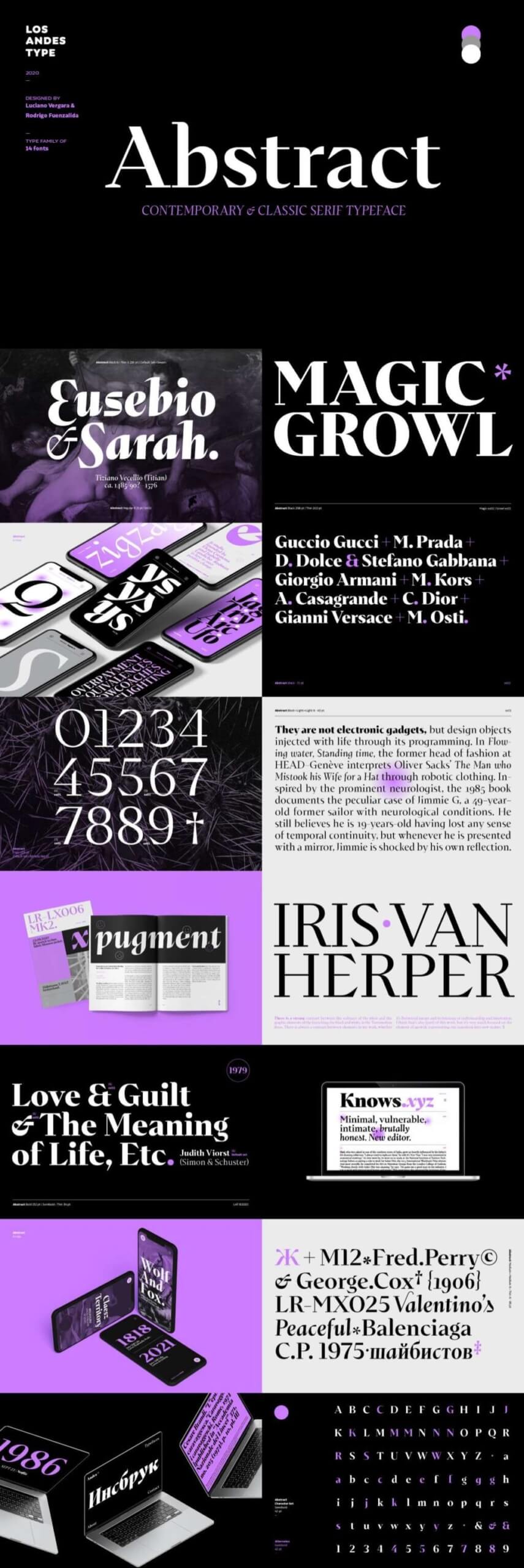
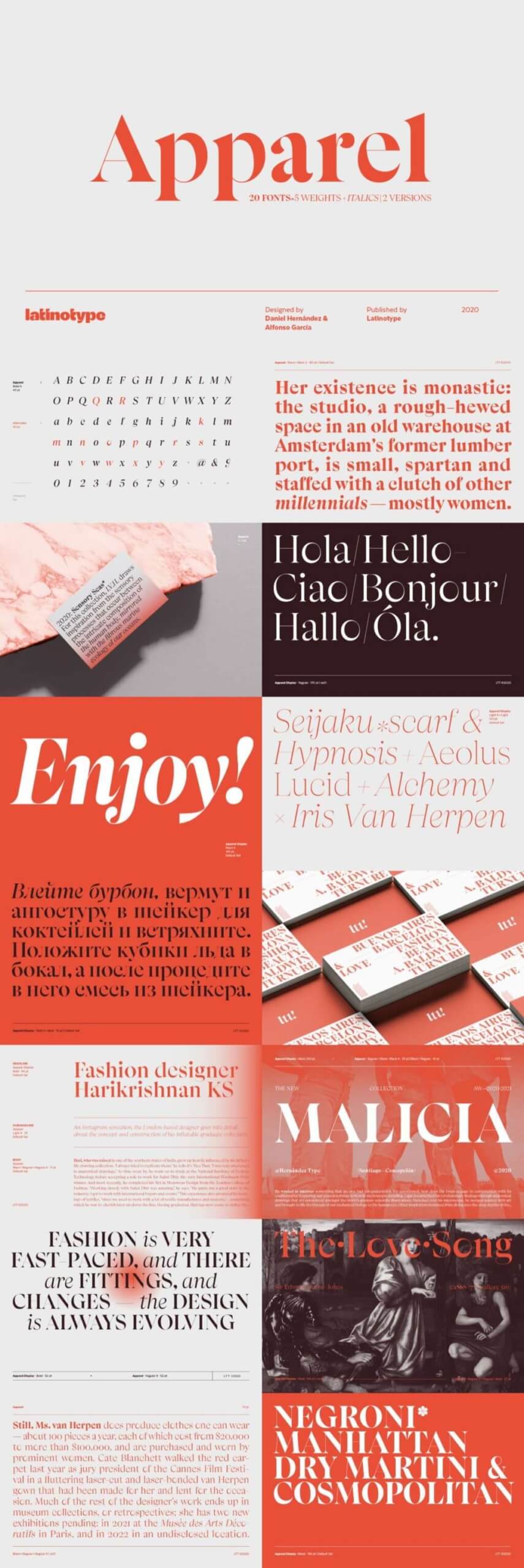
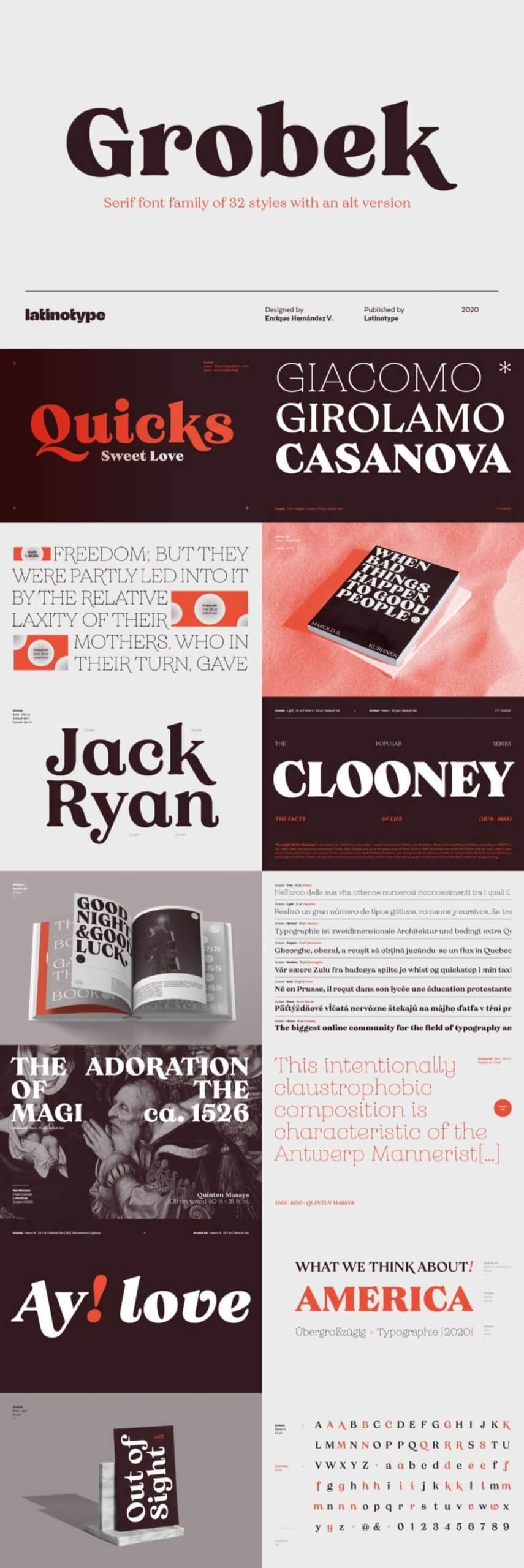
ウェイト違いが豊富なビッグファミリー書体
何種類ものウェイトをそろえたビッグファミリー書体は、繊細なウェイトの使い分けが必要なデザインワークで重宝します。The Treasure Trove of Fonts for Typography Loversも、そんな便利なビッグファミリーを収録。通常価格が300ドル以上のものも、このバンドルなら他のフォントとまとめて29ドルで揃えられます。
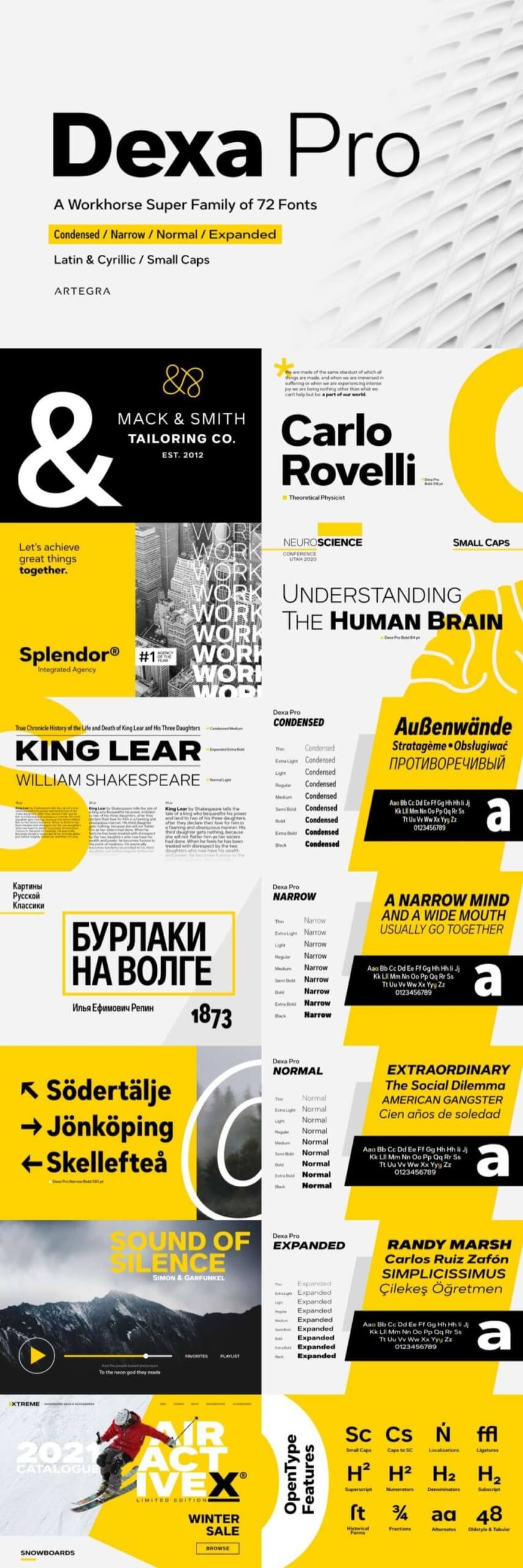
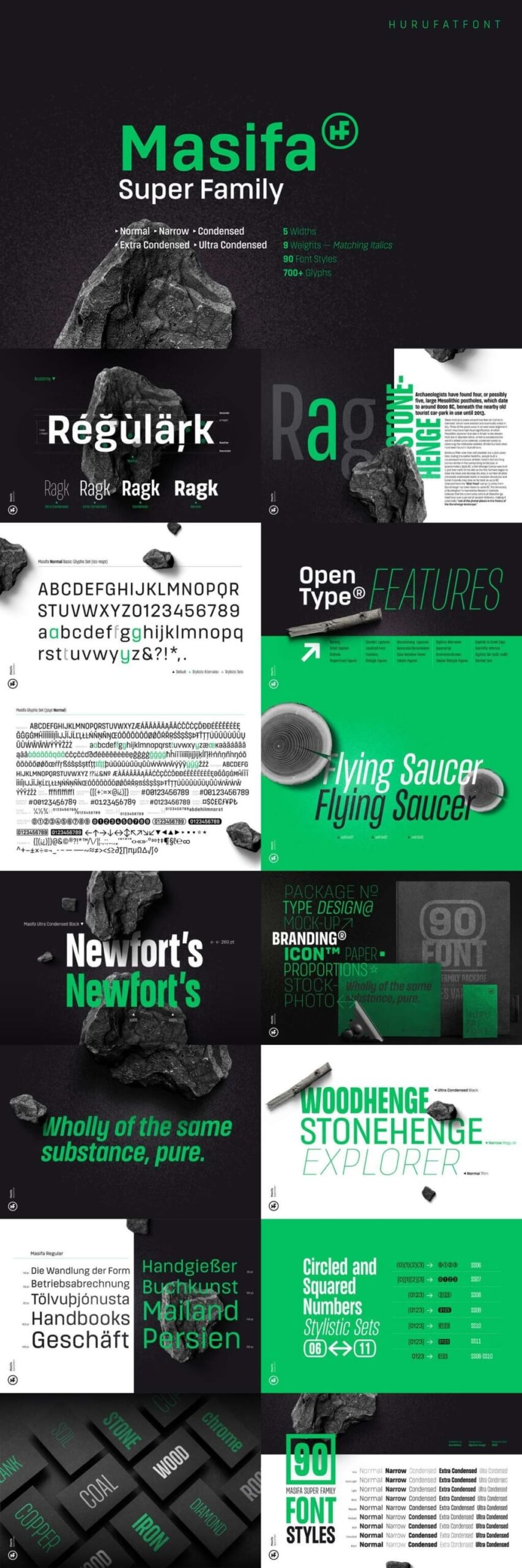
小さくても読みやすい!実用的なサンセリフフォント
小さい文字が多い媒体に便利なサンセリフフォント。The Treasure Trove of Fonts for Typography Loversにも様々なサンセリフフォントを収録しています。
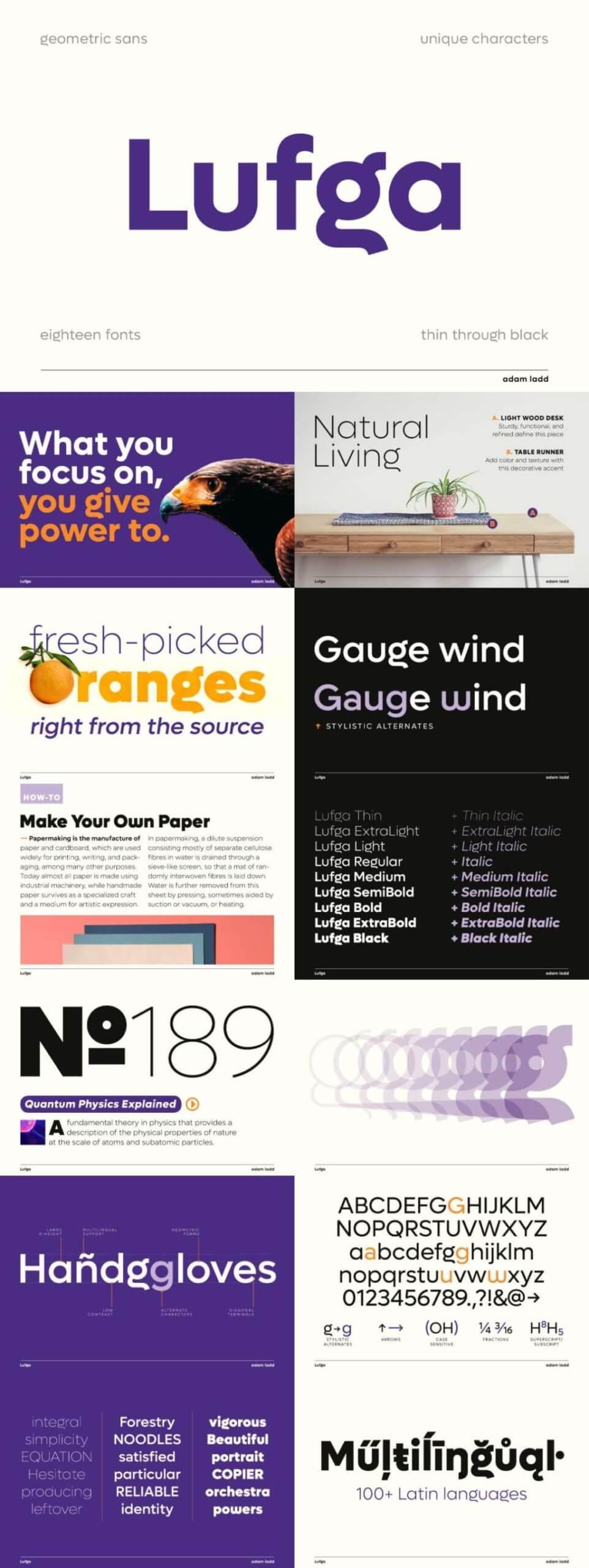
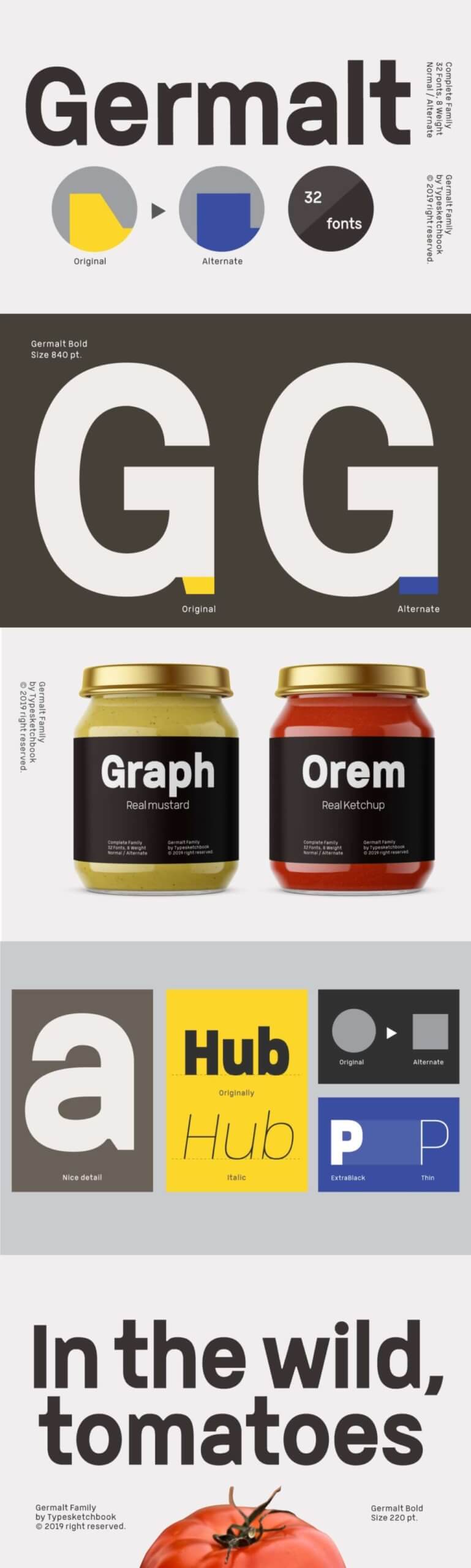
エレガントな曲線が魅力のスクリプトフォント
文字組に合わせて、複数用意された字形から最適なものが選べる手書き風スクリプトフォント「Hello My Love」。多言語対応で、ウェブフォントも収録しています。
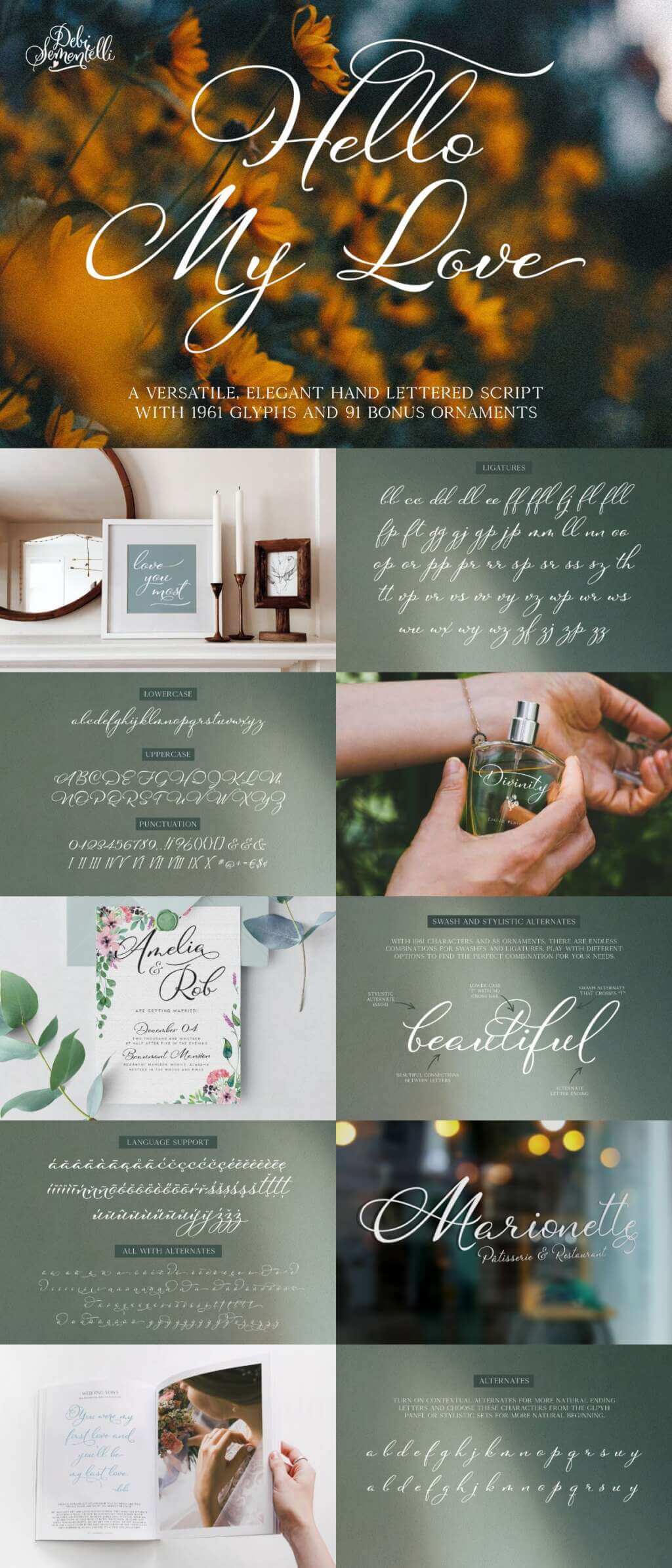
ペアリング済みのフォントセット
フォントの組み合わせを選ぶ手間から解放してくれるペアリング済みフォントセット「Omnipop」は、やさしい印象のサンセリフ、スクリプト、ブラシフォントを収録。ポスターやチラシ、メニューのデザインなど幅広く使えます。